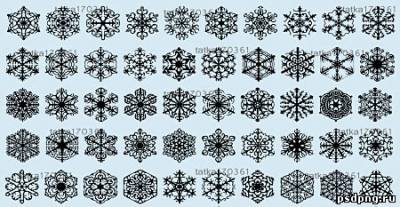
Fonts | Шрифт Новогодний шрифт — Снежинки By Lipka On Суббота, 27 августа 0 Поделиться Новогодний шрифт — Снежинки Делаете англ.раскладку и печатаете. Вместо английских букв и цифр печатаются снежинки. 2 TTF + jpeg | 150 снежинок | 10,6 mb Скачать с Depositfiles Скачать с UniButes Скачать с Turbobit 0 Поделиться FacebookTwitterReddItWhatsAppPinterestЭл. адресTelegramVKOK.ru Lipka 18750 posts 0 comments Предыдущий пост Шрифты — Новогодние картинки Новый пост 1000 каллиграфических, рукописных и печатных шрифтов Вам также может понравиться Еще от автора Fonts | Шрифт Коллекция русских шрифтов — На любой случай Fonts | Шрифт Шрифт Уолт Дисней Fonts | Шрифт Пак веб шрифтов Fonts | Шрифт Декоративные и рукописные шрифты для фотошопа и текстовых редакторов Prev Next Оставьте ответ Отменить ответВаш электронный адрес не будет опубликован. Save my name, email, and website in this browser for the next time I comment. Пожалуйста, введите ответ цифрами:5 × 4 = Δ Войти в систему Новости Как добавить материал на сайт? Видеоуроки онлайн Статьи Описание инструментов Основы работы Уроки Photoshop Установка дополнений Фотомонтаж онлайн Добро пожаловать! Войдите в свою учетную запись. Забыли пароль? Запомни меня Пожалуйста, введите ответ цифрами:15 − три = Если Вы - человек, тогда лучше оставить это поле пустым: Войти в систему Восстановите свой пароль. Пароль будет отправлен вам по электронной почте. Пожалуйста, введите ответ цифрами:3 + четырнадцать =